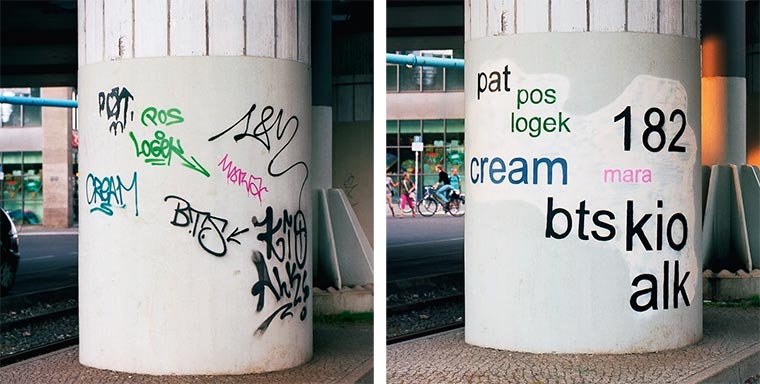
Graffiti-Tags mit sauberen Fonts ersetzen graffiti-paintover-fonts_01
Das feiere ich gerade sehr ab! „Das ist keine Kunst, das ist Geschmiere!“ oder „Wer soll das denn lesen können?!“. Die Graffiti-Kultur hat es nicht immer leicht. Werden aufwendige Murals gerne mal als Kunst „akzeptiert“, haben die traditionellen Tags einen eher schlechten Ruf. Auf imgur ist jetzt ein Album aufgetaucht, in dem scheinbar unleserlich dahin „geschmierte“ Tags in fein säuberliche Fonts übertragen wurden. So können auch das Büro-Weißhemd und Omi etwas damit anfangen. Herrlich!